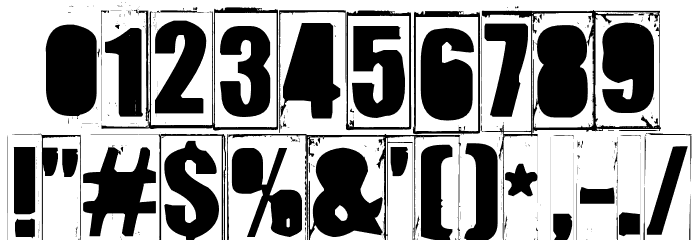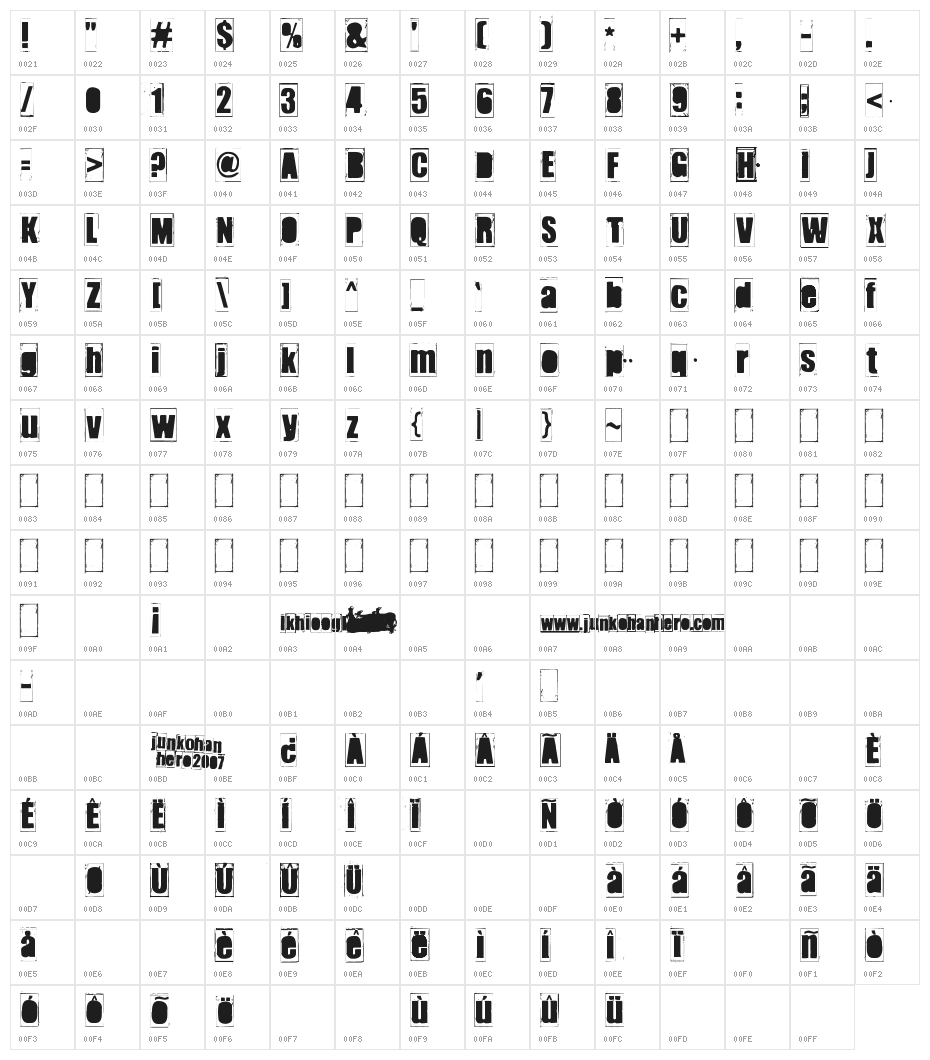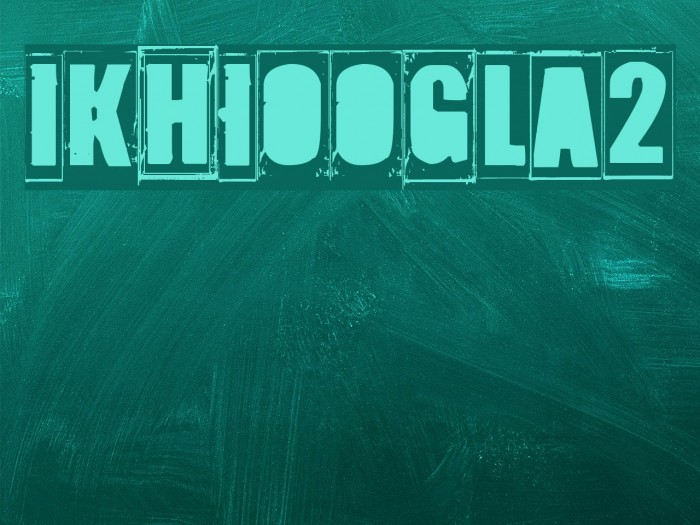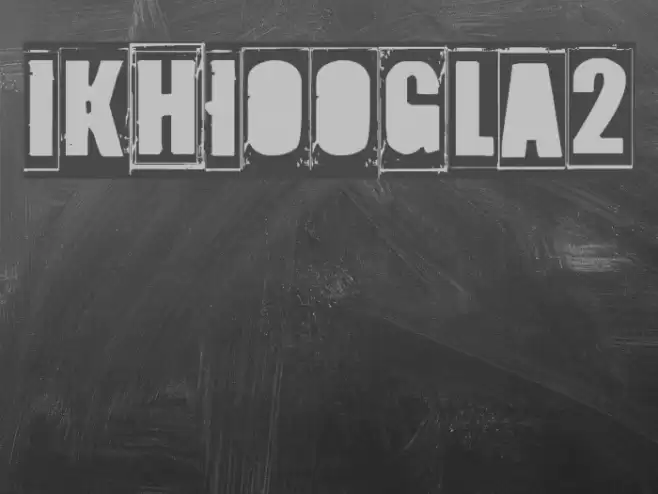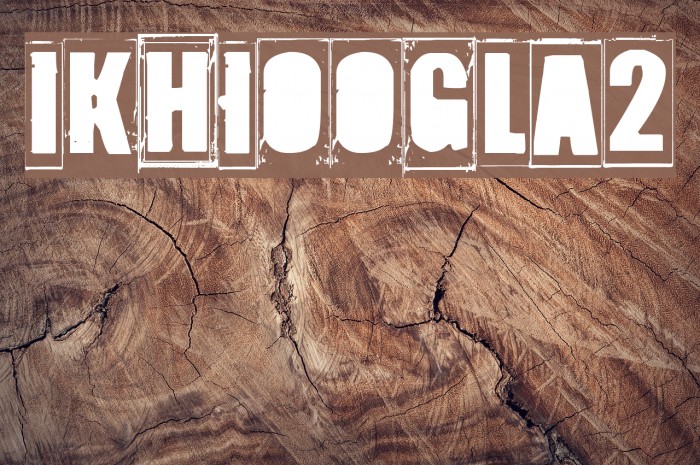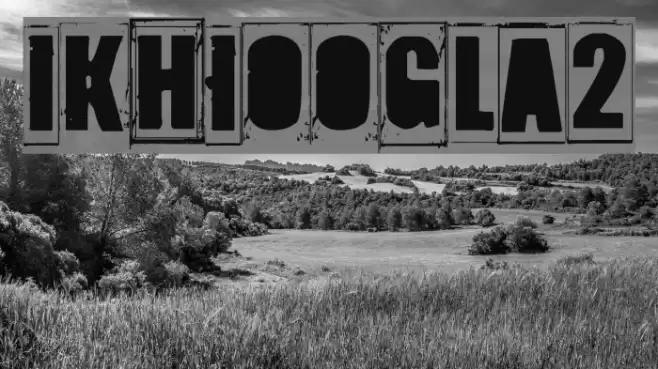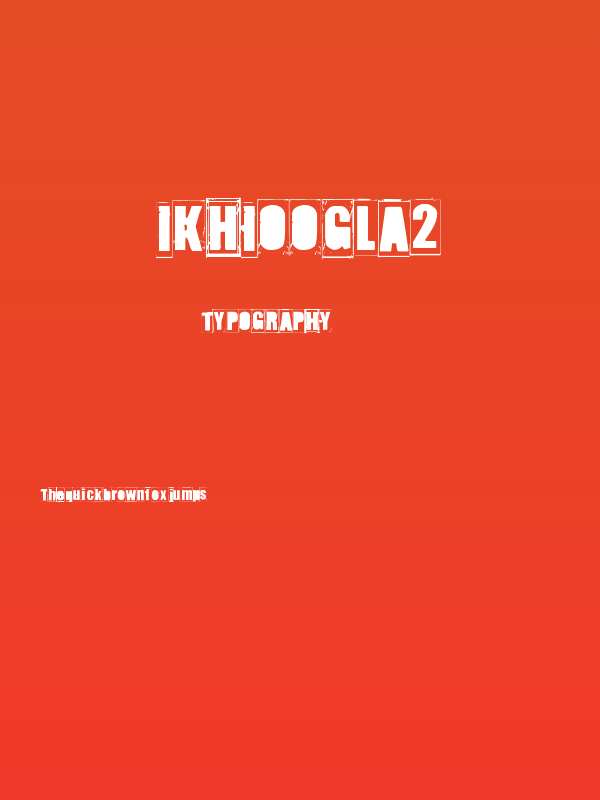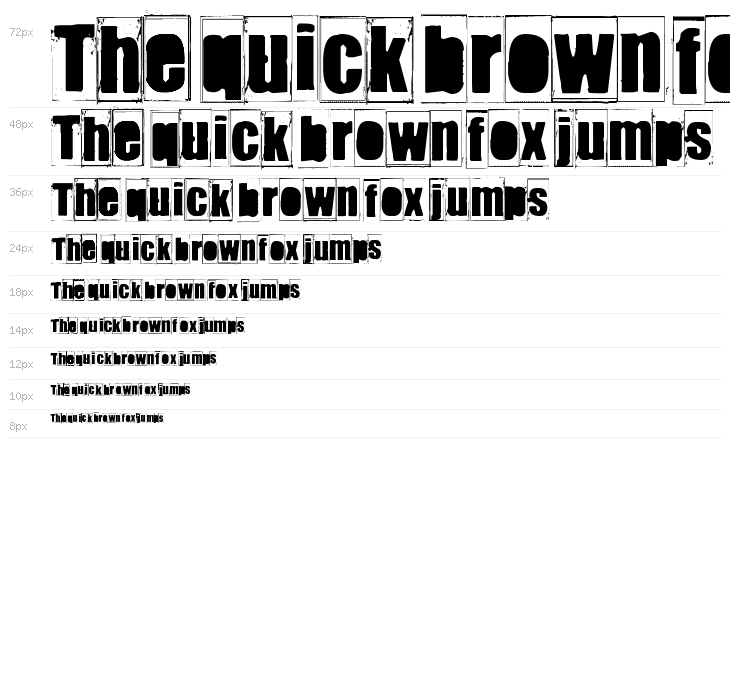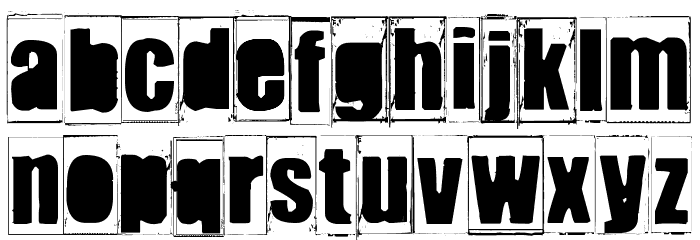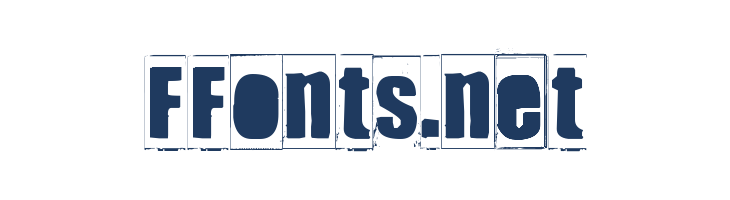
IKHIOOGLA2 Font
✎ Distorted Eroded
| Style général | Grunge, Distressed |
| Projets proposés | Ideal for posters, album covers, branding for edgy or alternative products, and any design needing a strong, impactful visual statement. |